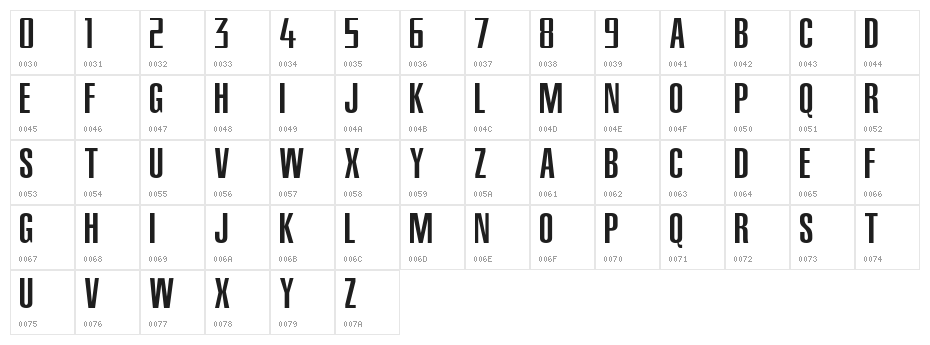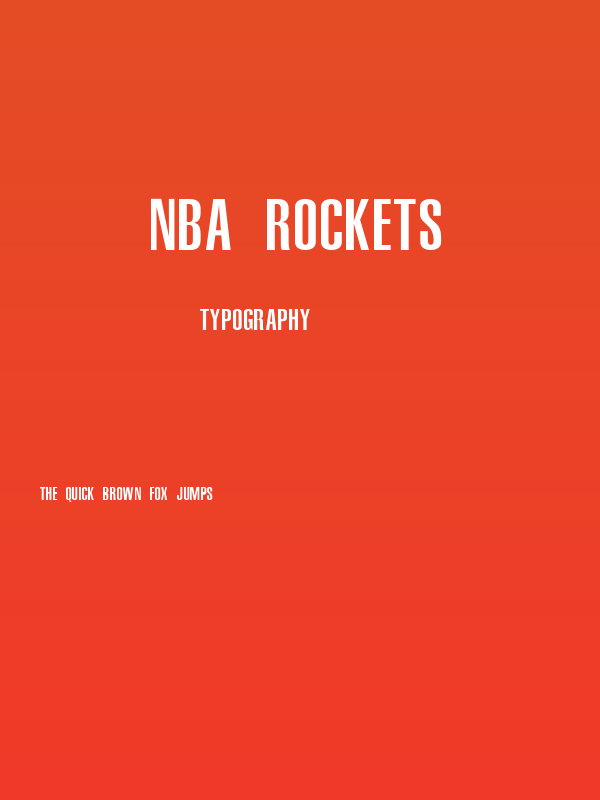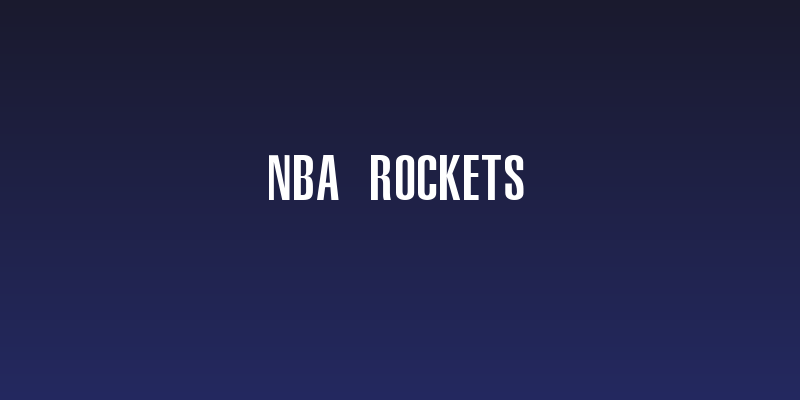
NBA Rockets Font
| Рекомендуемые проекты | This font is perfect for sports branding, posters, and any project requiring a bold, modern typeface that commands attention. |